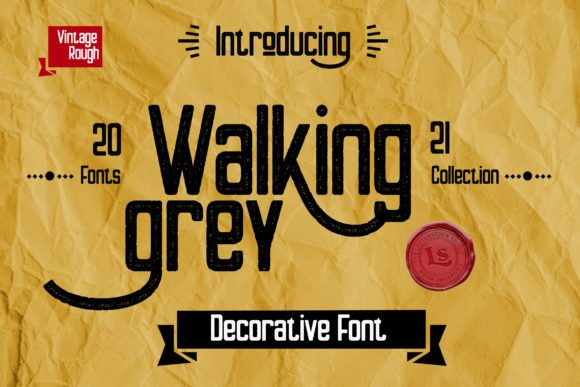
[Creativefabrica] Walking Grey Font (2021)
Walking Grey - это крутой, грубоватый шрифт с идеальной долей модности.
Используете ли вы его для крафтинга, цифрового дизайна, презентаций или создания поздравительных открыток - он идеален!